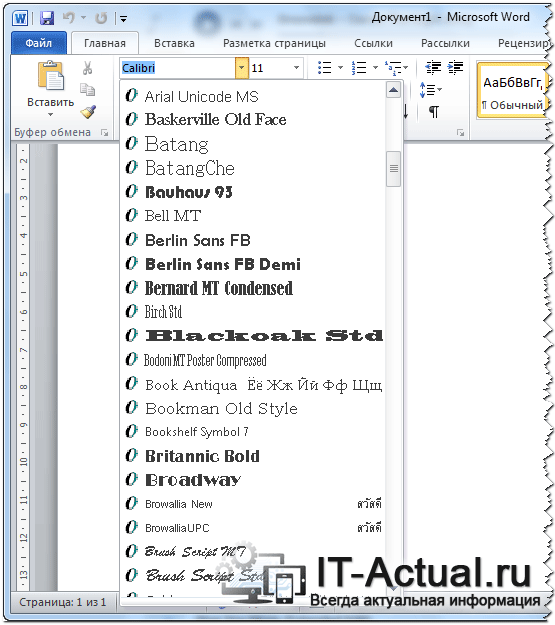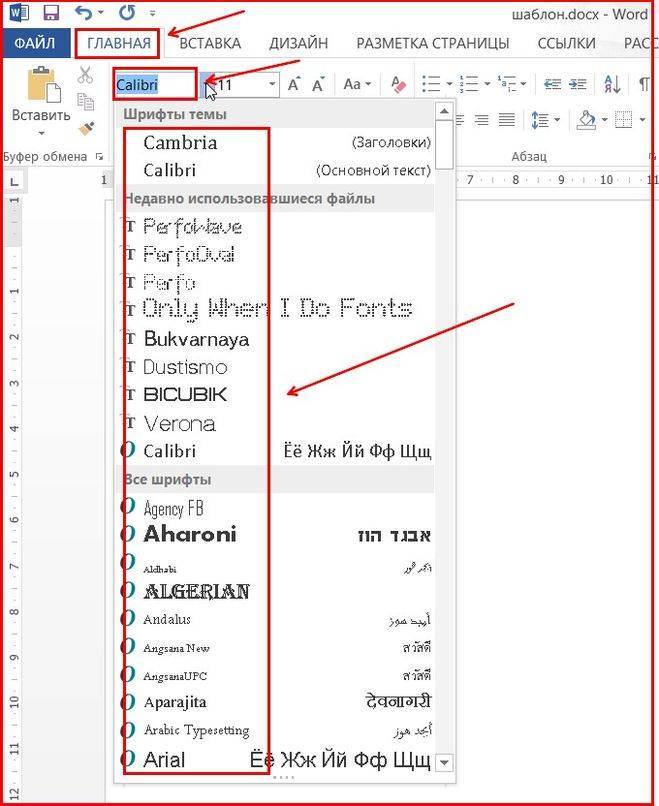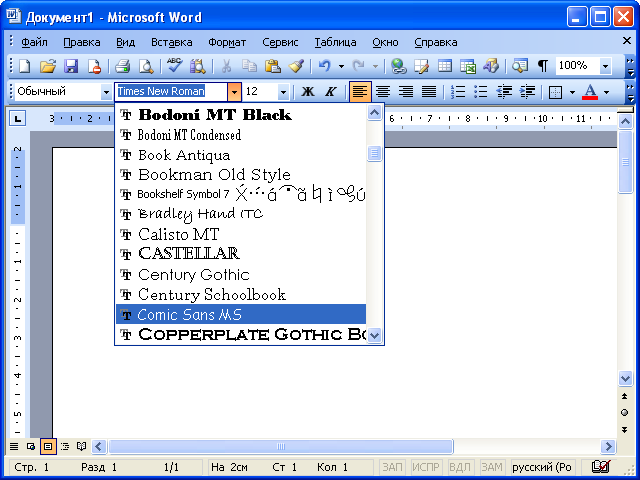
Шрифт классический в ворде: Требования к оформлению статей
Какой стандартный шрифт используется в документах
Doc или. docx) стандартным шрифтом Times New Roman (14 пт.) с межстрочным интервалом — 1,5, отступ «первой строки» — 1см.
Какой шрифт является стандартным
Arial. Arial — стандартный шрифт для рабочих станций под управлением Windows. и один из наиболее широко используемых шрифтов без засечек (что означает отсутствие маленьких черточек в конце каждой буквы).
Какой шрифт использовать в ворде для документов
Шрифт — Times New Roman. Размер шрифта основного текста (кегль) — 14 (Формат → Шрифт → Размер 14). Размер шрифта в подстрочных ссылках — 12.
Какой шрифт нужен для документов
Вид шрифта — calibri, times new roman. Величина букв — четырнадцатый, допускается двенадцатый размер. Текст обязательно равняется по ширине, каждый абзац имеет отступ на полтора сантиметра.
Какой шрифт используется в паспорте РФ
Машиночитаемая запись вносится в паспорт специальным принтером с использованием шрифта OCR-B type 1 (Стандарт ИСО 1073/II). Для заполнения позиций знаков нижней строки машиночитаемой записи используется цифровой способ кодирования информации, кроме позиций знаков 11 — 13 и 21.
Какой шрифт по госту
1.1 При оформлении документа для основного текста используют гарнитуры шрифта Times New Roman размером 14 пунктов или Arial размером 12 пунктов, для приложений, примечаний, примеров и сносок — гарнитуры шрифта Times New Roman размером 12 или Arial размером 11.
Как называется классический шрифт
Стандартные шрифты для дизайна
# | Шрифт | Семейство |
|---|---|---|
1 | Arial | sans-serif |
2 | Arial Black | sans-serif |
3 | Comic Sans MS | cursive |
4 | Courier New | monospace |
Как оформить документ в ворде по госту
Основные правила оформления:
- Текст набирается исключительно шрифтом Times New Roman.
- Стандартный размер шрифта основного текста — 14 пт.
- Межстрочный интервал — полуторный.
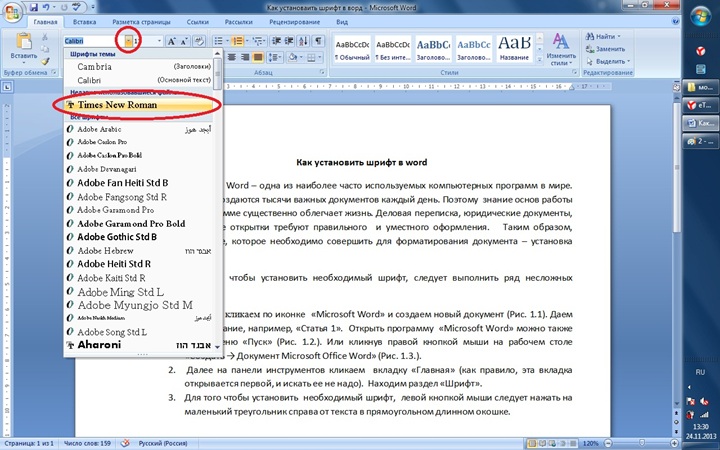
- Размер полей: правое не менее 10 мм, верхнее и нижнее — не менее 20 мм, левое — не менее 30 мм.
- Абзацный отступ — 1,5.
Какой шрифт используется для официальных писем
Наиболее распространенный шрифт деловых писем — Times New Roman. Использование этого шрифта гарантирует отсутствие проблем с кодировкой писем при отправлении по электронной почте.
Какой шрифт в ворде по умолчанию
Действия по шагам (1, 2, 3, 4), чтобы сменить шрифт по умолчанию в редакторе Word. На рисунке 1 показано зеленой линией, что шрифтом по умолчанию является Calibri (Основной текст), размер 11.
Какой шрифт используется в заявлениях
В госте указаны правила оформления электронных документов: Нужно использовать шрифты Times New Roman, Arial, Verdana или Calibri. Оптимальный размер — 12—14. Адресата или само слово «Заявление» можно выделить полужирным.
Какой шрифт лучше использовать
10 лучших шрифтов для вашего сайта 2020 года:
- Playfair Display.
Со времен просвещения в конце 18-го века широкие перья были заменены острыми стальными ручками. - Bebas Neue. Bebas Neue свободный sans serif, создан Ryoichi Tsunekawa.
- Druk Wide.
- Cinzel.
- Gilroy.
- Montserrat.
- Proxima Nova.
- PT Sans.
Какой шрифт лучше всего
Основной вывод: не существует одного лучшего шрифта для всех пользователей По результатам исследования наиболее высокую скорость чтения продемонстрировал шрифт Garamond — 312 слов в минуту. Самым же «медленным» шрифтом из 16 протестированных оказался Open Sans — 254 слов в минуту.
Какой шрифт используется в справках
➤ Как оформлять кадровые документы по новому ГОСТу
Как правило, принято в Организациях, большинство документов оформляются шрифтом «Times New Roman», размер шрифта составляет 12-14. Такие же требования предусмотрены ГОСТ Р 7.0.97-2016.
Caslon Classico
Caslon Clasico разработан Франко Луином в 1993 году, вдохновлен шрифтом Уильяма Каслона в 16 th век. Это семейство шрифтов известно как королевский шрифт, который дал жизнь другим политическим шрифтам с чистым и профессиональным подходом.
Bembo
Bembo разработан Альдусом Манутиусом, Фрэнком Хинманом Пьерпонтом и Франческо Гриффо в 1929 году.
Простой тому пример — один из четырех доступных типов шрифта Arial (показан на скриншоте).